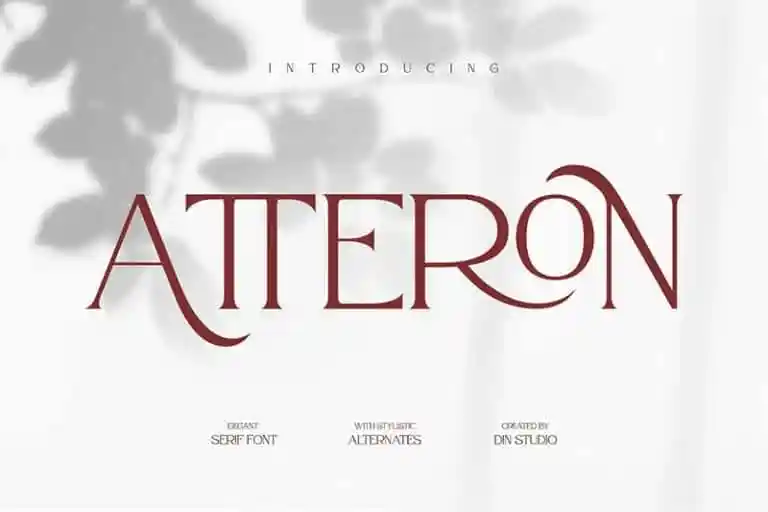
Atteron Serif Font – Download Grátis
A fonte Atteron Serif é uma tipografia serifada com toques modernos e simplificação clássica. Ela surgiu dos designers de fontes chamados Din Studio, e é projetada para criar um forte senso de letra serifada e um feeling de luxo. Inspirada em fontes textuais clássicas e tendências tipográficas atemporais, a Atteron Serif é perfeita para criações de logomarcas, identidades empresariais e citações. Cada caractere possui uma marca única e bela, tornando-a um recurso visual único para designers profissionais em busca de uma fonte que seja tanto versátil quanto elegante.